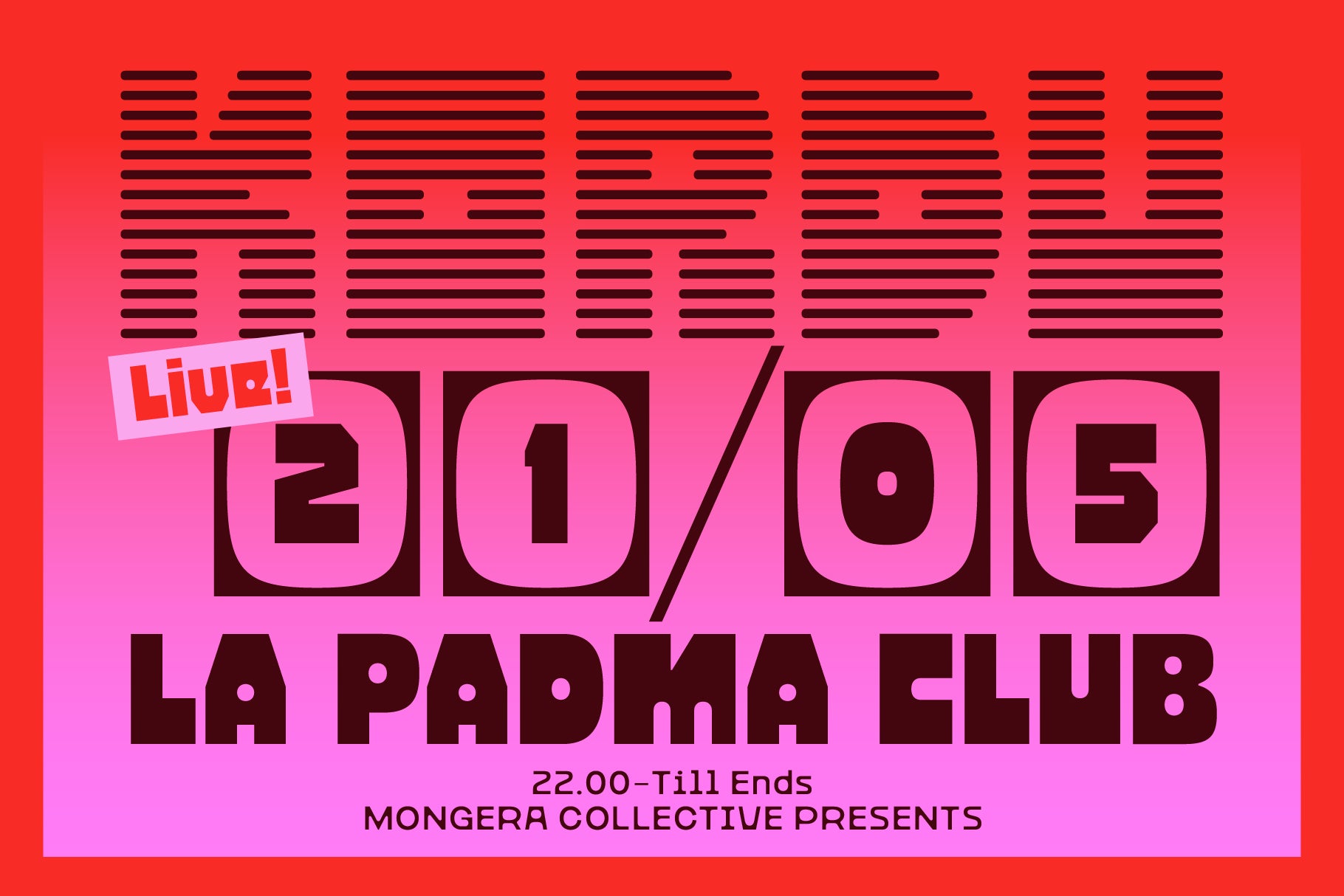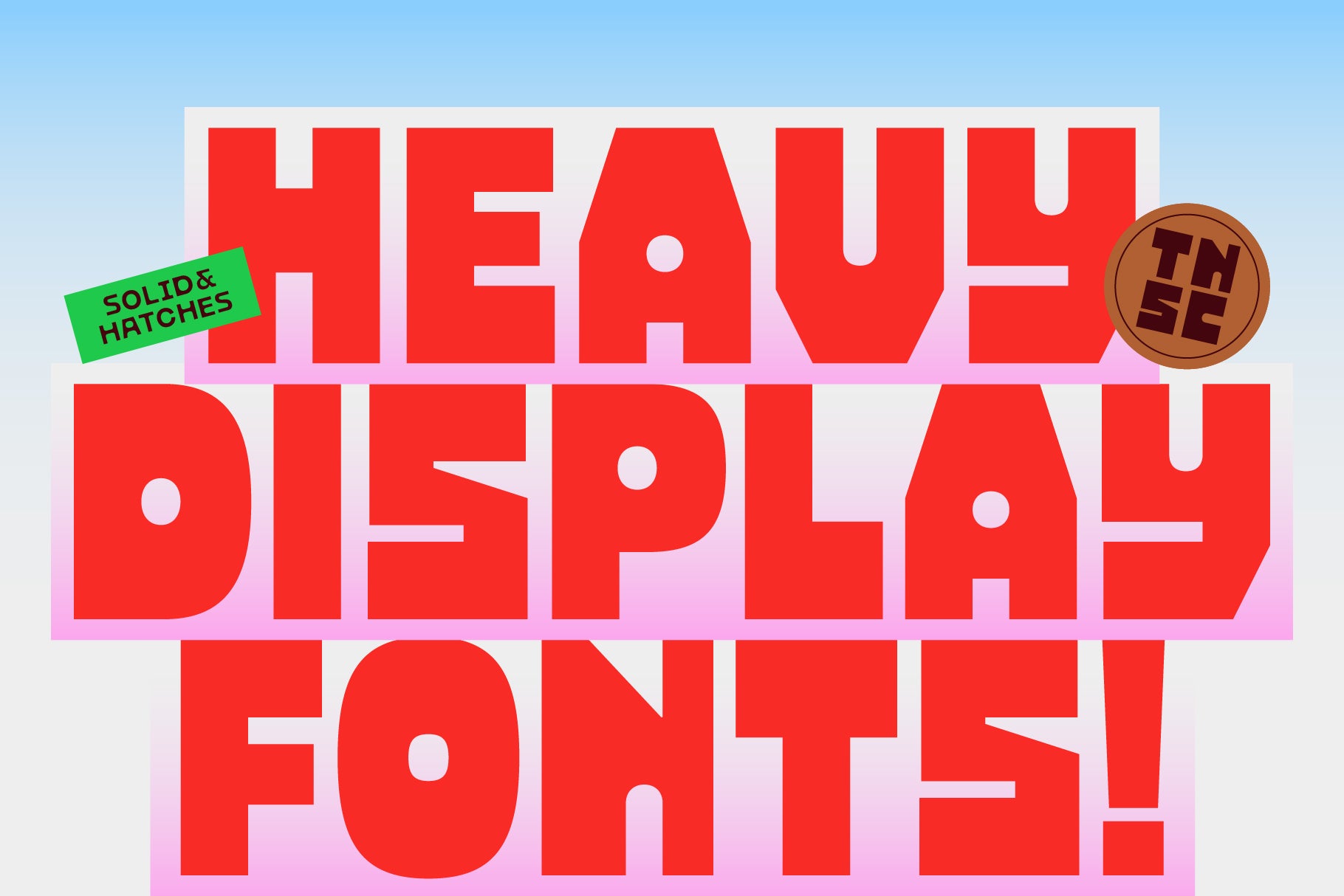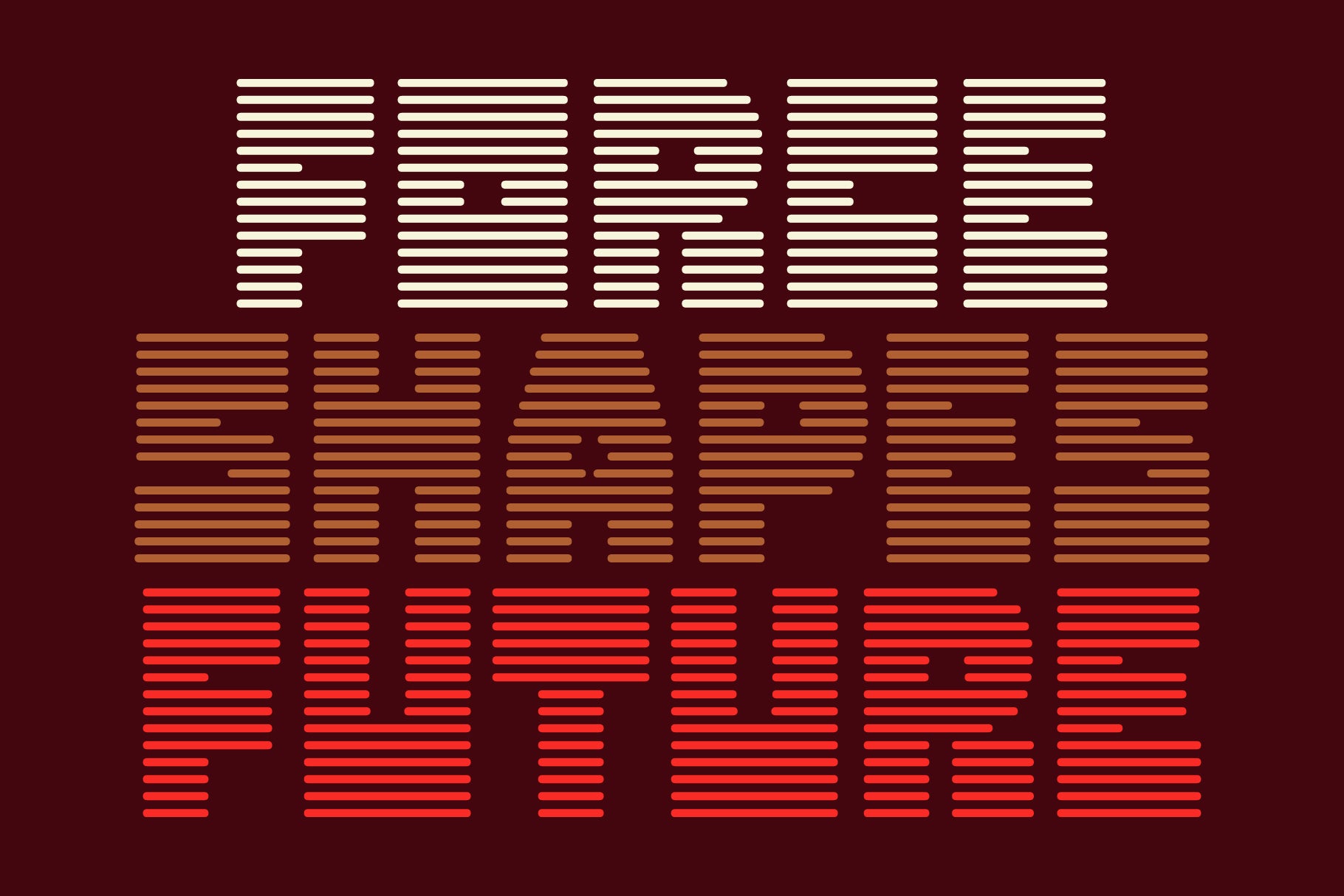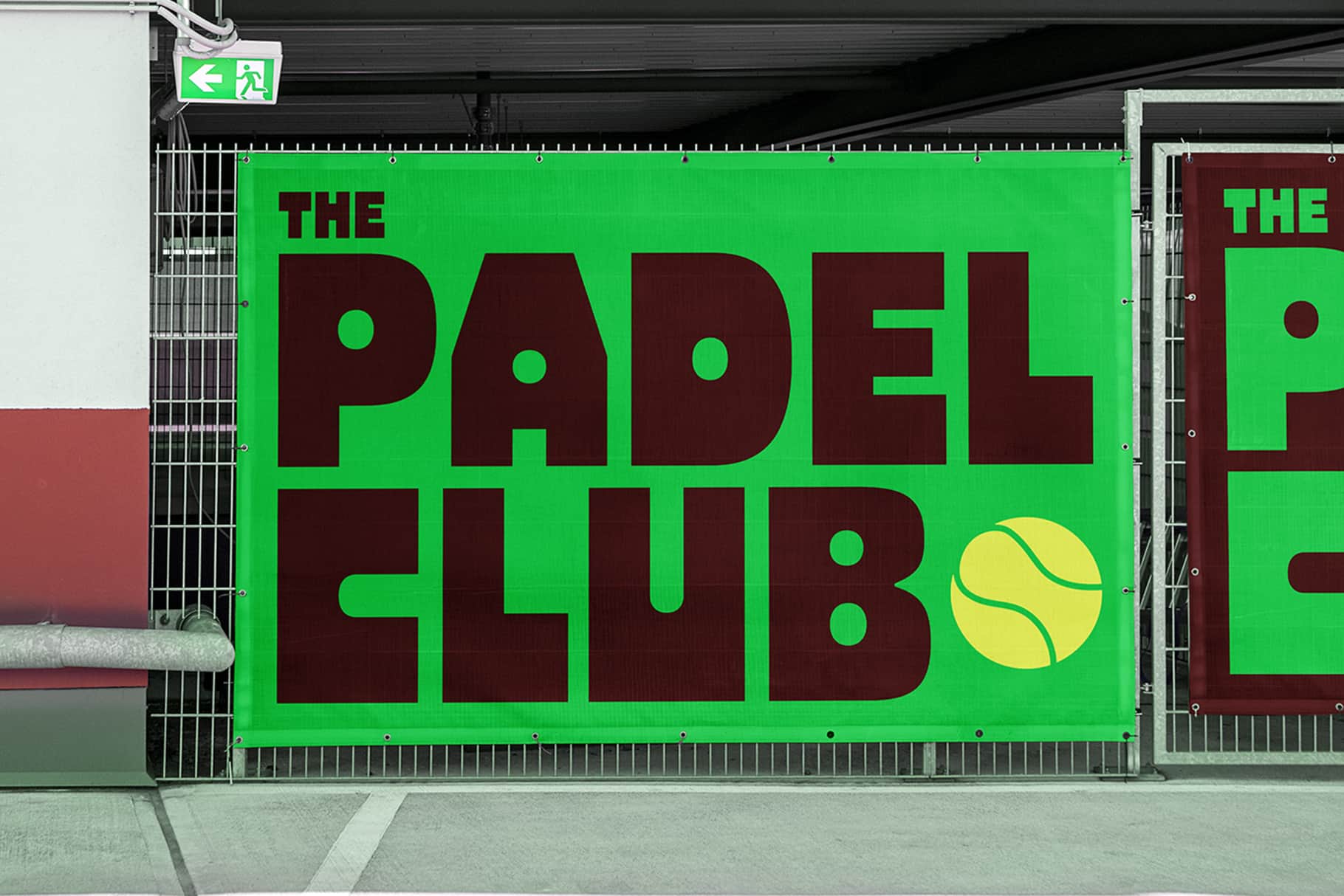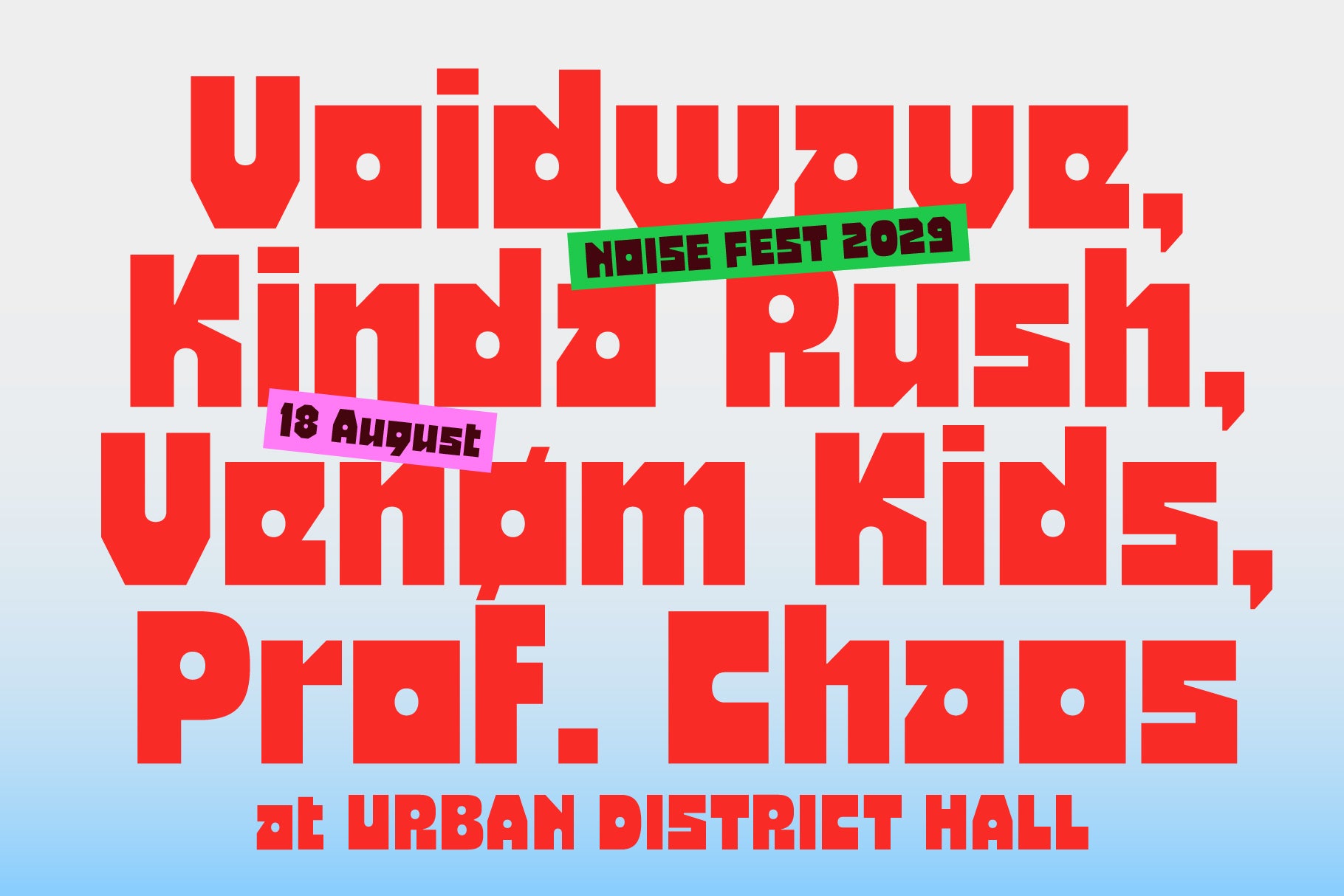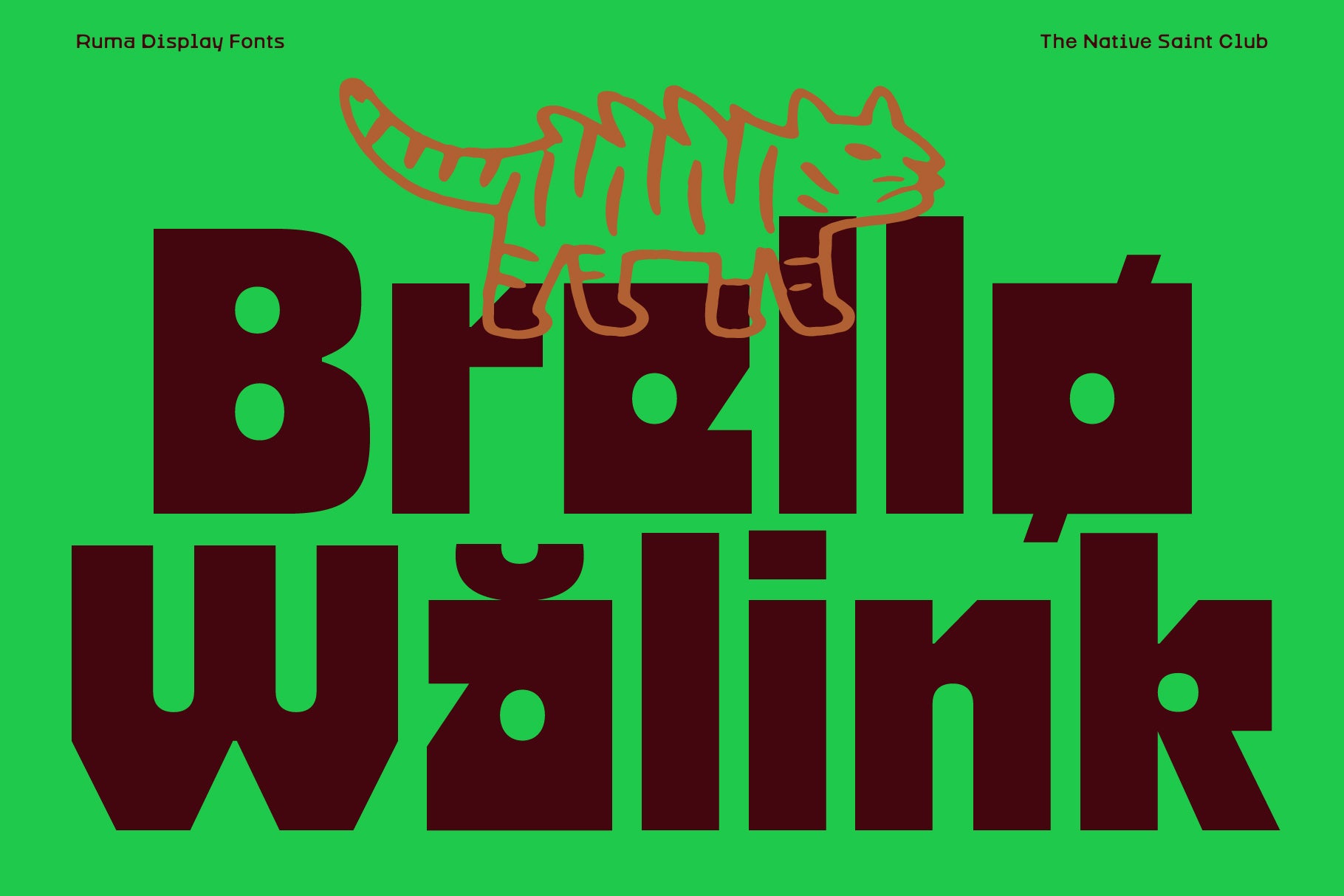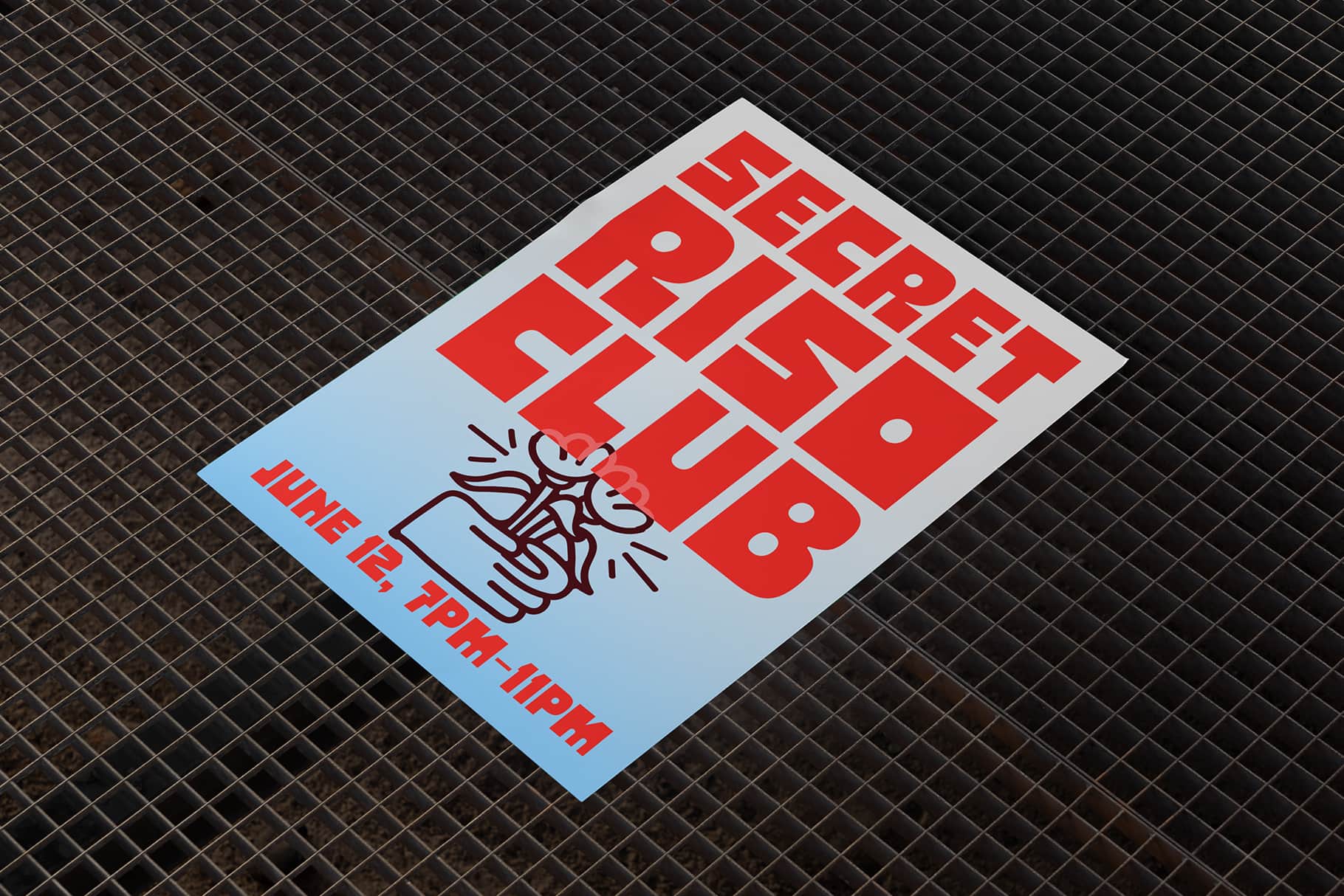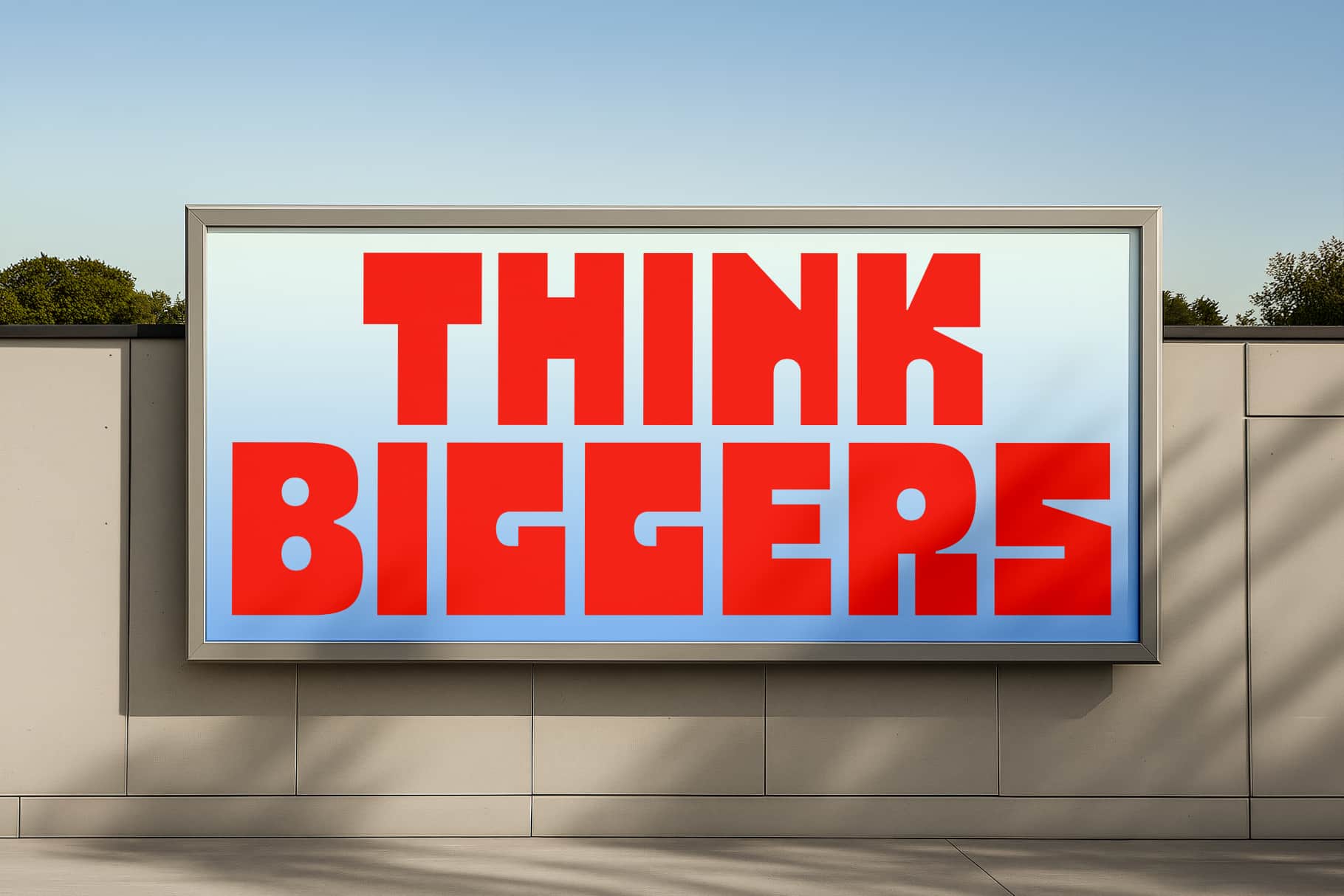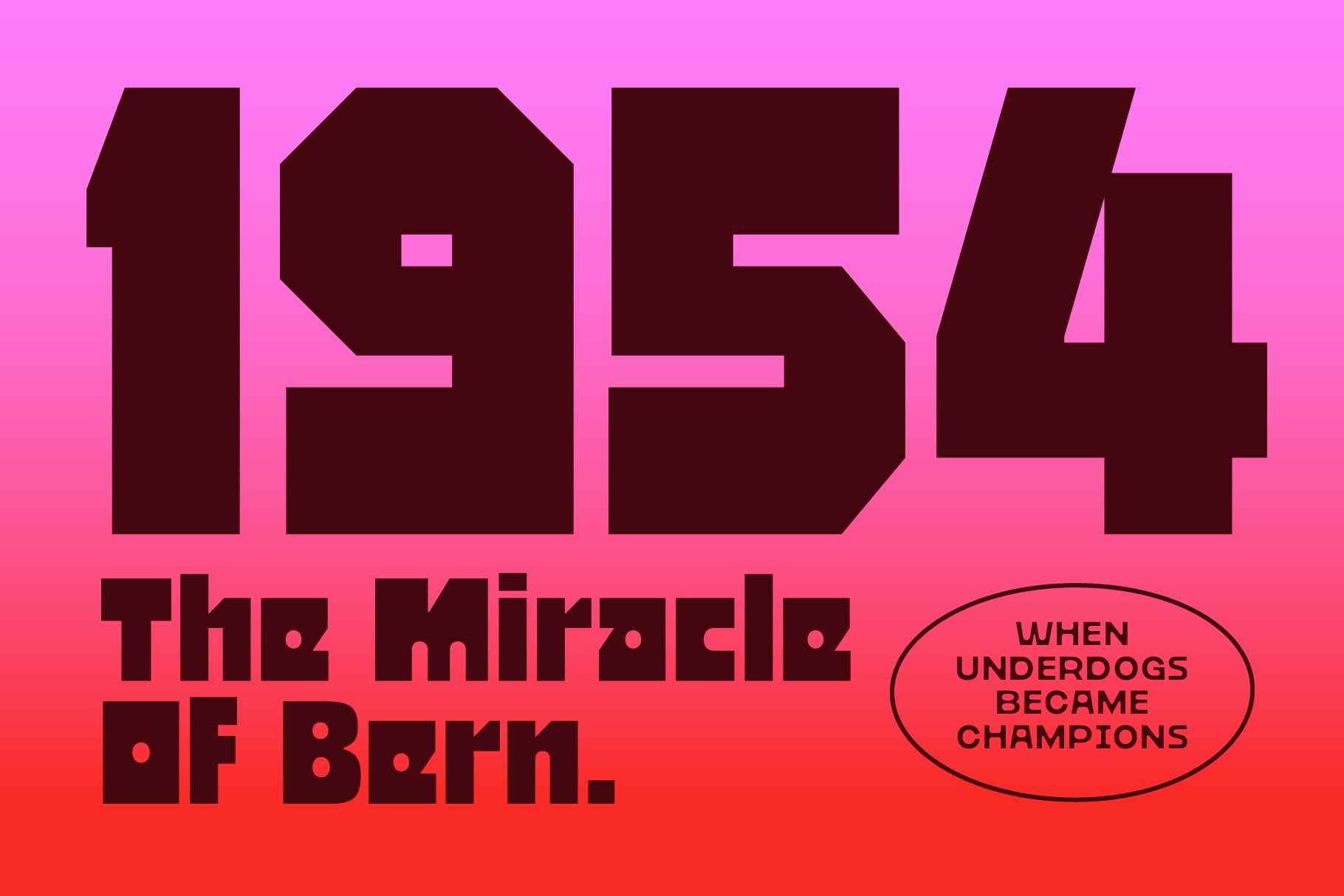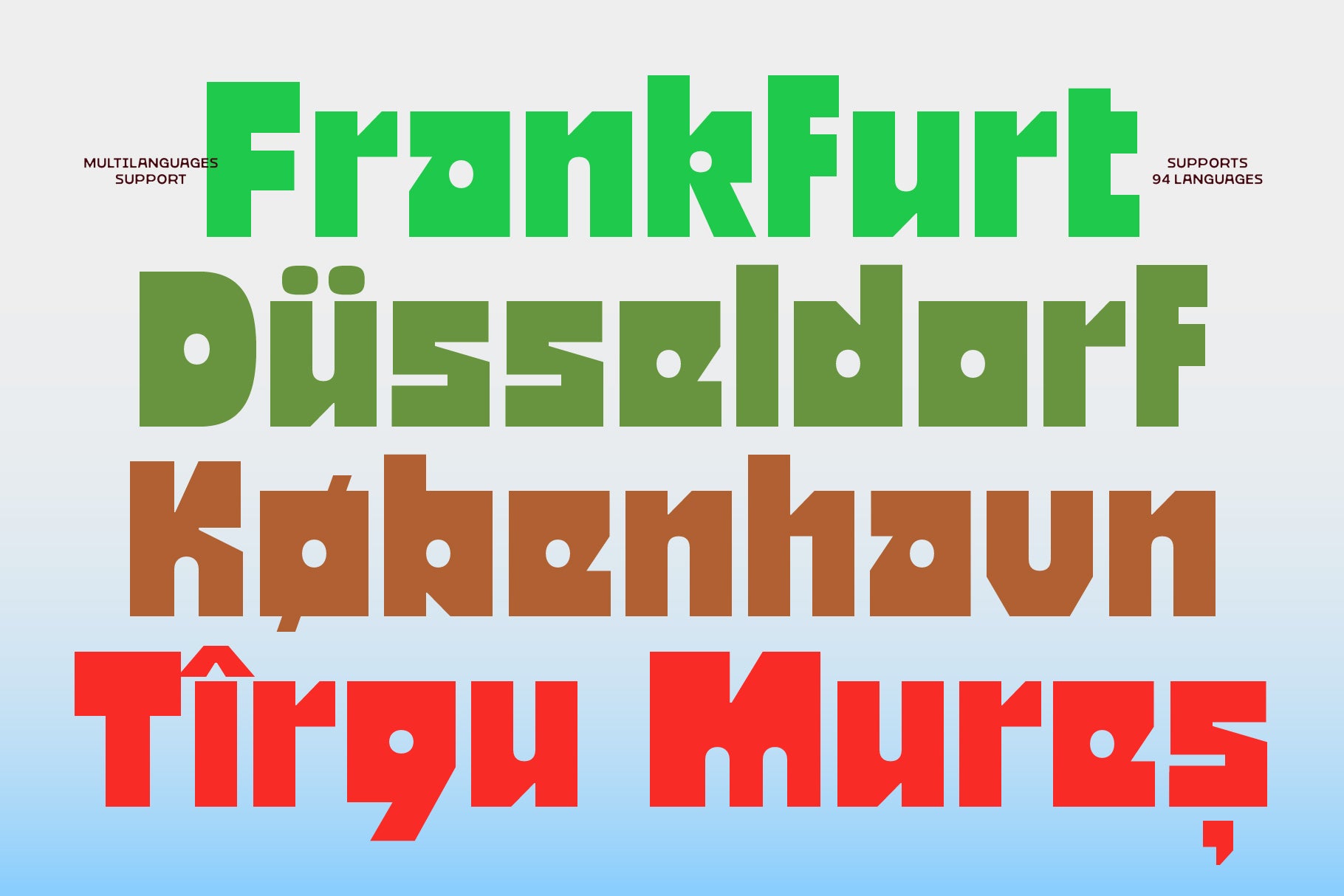
Tipografía Ruma TNSC
Ruma es una audaz tipografía de exhibición construida en torno a formas geométricas fuertes y formas de glifos pesadas diseñadas para dominar a escala de exhibición. Cada carácter está construido con un peso deliberado y precisión — lo suficientemente distintivo como para funcionar como un elemento gráfico por derecho propio, no solo como un portador de lenguaje.
Viene en dos estilos — Sólido y Rayado (Hatch) — dándote la opción entre pura masa y textura interior gráfica. Perfecto para carteles, branding, empaques, titulares y visuales de estilo urbano donde la tipografía necesita mantener su terreno frente a imágenes audaces y colores saturados.
Características
• 509 Glifos
• 2 Estilos (Sólido, Hatch)
• Minúsculas
• Mayúsculas
• Diacríticos
• Números (5 conjuntos)
• Puntuación
• Símbolos
• Moneda
• Matemáticas
• Flechas